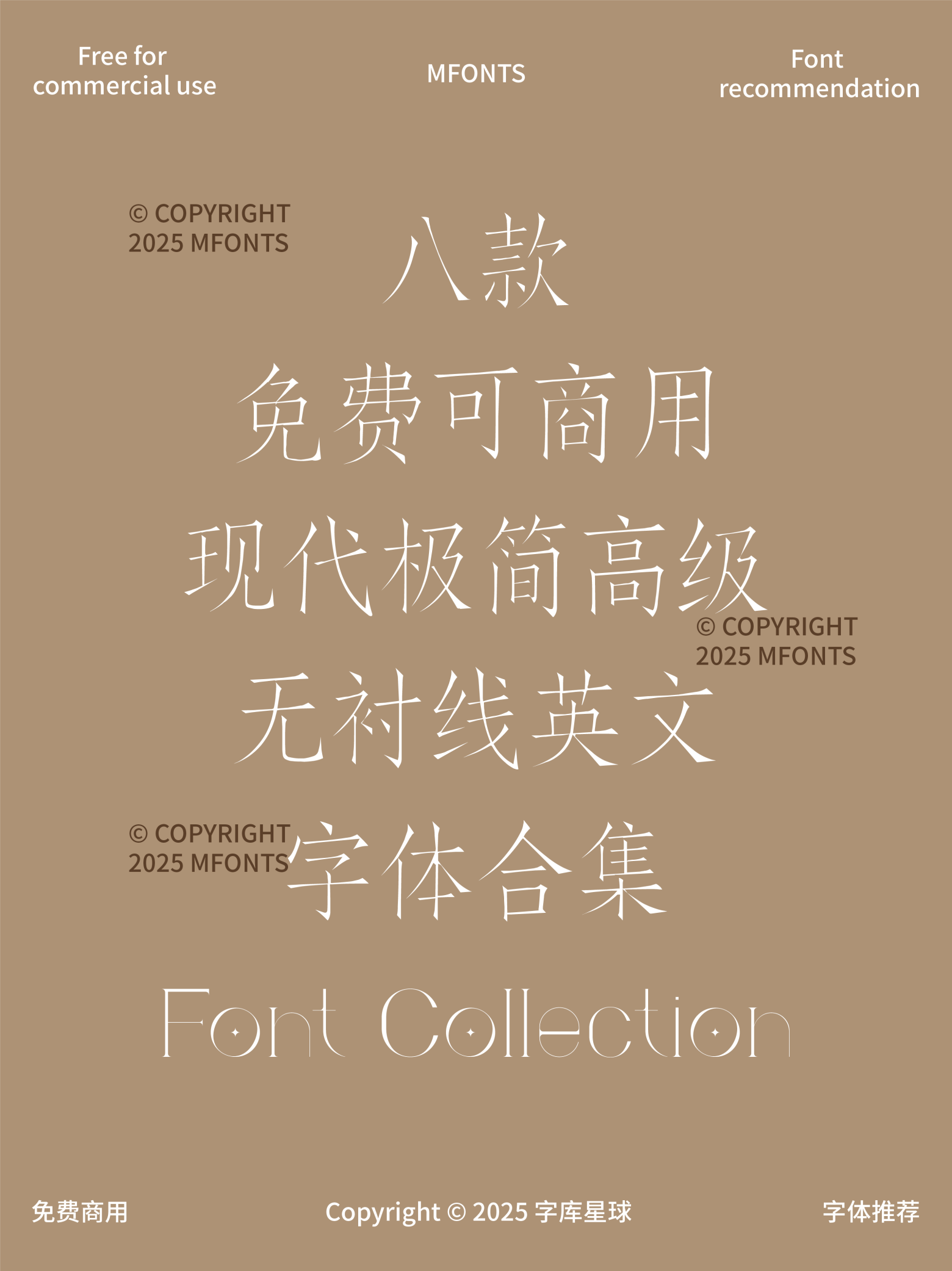
八款免费可商用现代极简高级无衬线英文字体
今天给大家分享 8 款超赞的免费可商用现代极简高级无衬线英文字体,轻松让你的作品瞬间高级。
典型的现代简约风,笔画粗细均匀。文字排版独特美观,特别适合突出产品简洁特性,为电子产品展示图增添科技感与时尚感。优雅现代,衬线精致,字符间距舒适。时尚、美妆产品搭配它,精致感爆棚,尽显独特品味与魅力。